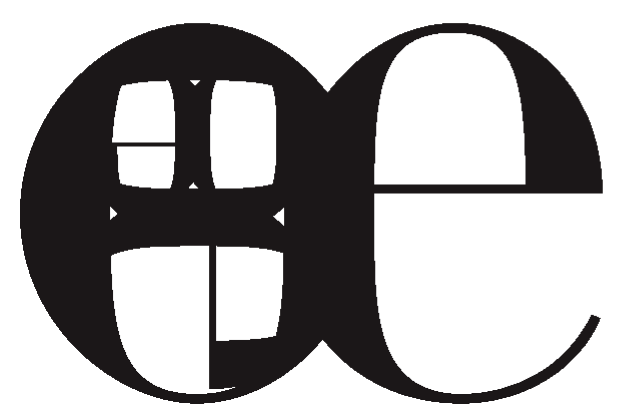
> En France, c'est l'AFNOR, qui sans consulter qui
> que ce soit, a décidé que le « ¦ » était sans
> utilité.
un peu simpliste comme histoire. voir
(réponse tardive pour cause d'exploration archéologique dans des archives bientôt « datables » au Carbone 14)
Merci pour vos excellentes (Cahiers GUTenberg obligent !) précisions.
Mais (cependant, toutefois & néanmoins...)...
L'histoire - hélas - n'est peut-être pas si simpliste, et semble remonter à (au moins!) début 1999 .
Et je suis allé un peu vite en écrivant AFNOR, quand, en réalité, il s'agissait de l'instance internationale.
Et les infos se recoupent, donc.
Voici-dessous les Mél./courriels échangés à l'époque avec l'AFNOR et le ministère de la culture (les correspondant ayant formulé leurs réponses à titre privé, je m'autorise donc à ne pas publier leur identité personnelle).
[...] nous vous informons qu'il n'y a pas au niveau de l' AFNOR de projet disponible concernant la suppression du digramme «e dans o». Des discussions au niveau international sont en cours au sujet dudit digramme mais restent non abouties et ne concernent que l'aspect échanges de données informatisées.[...]
[] Nous sommes concerné par ce problème qui - hélas - n'a pas eu jusqu'ici de solution simple. Ceci provient du fait que l'HTML 3.2 (le langage du Web) qui était jusqu'à ces derniers temps en vigueur, ne connaît comme jeu de caractères que l'ISO 8859-1 (ou ISO Latin 1) qui ne comporte pas le «e dans l'o».La petite histoire - ou la rumeur - raconte que le jour du vote à l'ISO le représentant de la France ne s'est pas présenté et que l'ISO à alors considéré qu'il s'agit d'une simple ligature facultative et a préféré inclure le thorn islandais qui lui estindubitablement une lettre !Néanmoins tout n'est pas perdu. La nouvelle version d'HTML, la 4.0 se réfère maintenant non plus à l'ISO Latin 1 mais à l'Unicode (jeu de 65000 et quelques caractères codés sur 2 octets). Le «e dans l'o» y a sa place (son code) et rien ne s'opposerait à son emploi généralisé. Si ce n'est qu'il faudrait disposer en théorie d'une police Unicode.Par chance, il se trouve que les polices Windows sont en fait un léger surensemble de l'ISO Latin 1. Celà au prix d'une extension de caractères graphiques à la place de caractères de contrôle. Mais, felix culpa, le«e dans l'o» y est inclus, en capitale et bas de casse, et les navigateurs récents sont capables de trancoder le code Unicode de ces deux caractères pour les afficher correctement.La situation est analogue sur MacOS où le jeu mac-roman comporte aussi ces caractères.Donc nous veillerons à ce que désormais le codage de ce caractère soit réalisé correctement. Le prix à payer est que le rendu sur les anciens navigateurs soit quelque peu barbare ![...]
Bref, préparant justement à l'époque une communication sur « ¦ » (si la ligature supporte, finalement et pour chacun(e), le voyage par internet !) et sur les signes (et le sens) en voie de disparition, j'ai ainsi réorienté le travail en cours (!) :
http://thierry.vohl.free.fr./%3f1+2+3.pngCes « figures » (dont les approches sont assez impossibles à régler) ne sont pas faites pour se voisiner de si près.